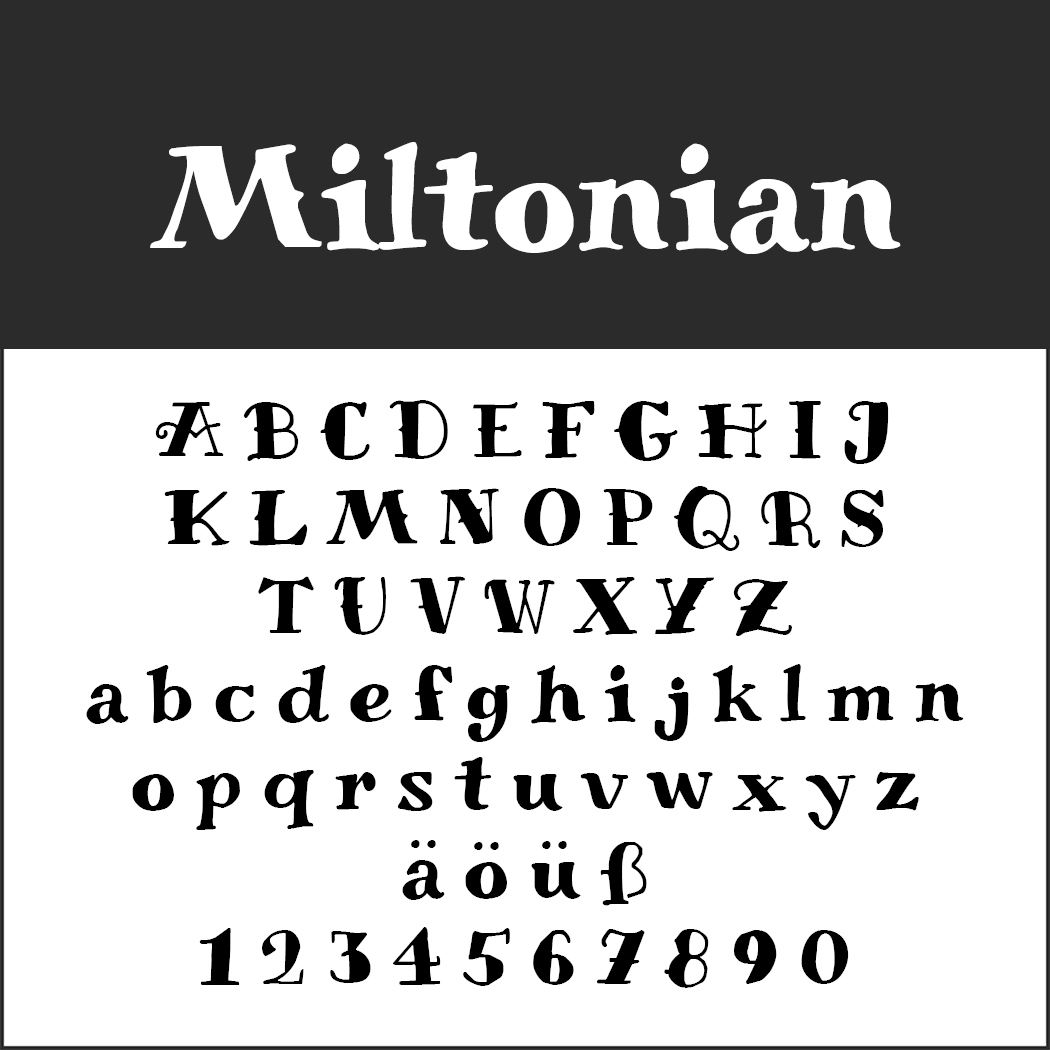
Haltung zeigen oder das eigene Lebensmotto nach außen tragen: Buchstaben werden heute nicht mehr nur gebraucht, um den Namen der Lieben auf dem Körper zu verewigen. Um so mehr Bedeutung gewinnen die Tattoo Schriftarten, mit denen die Textbotschaften auf die Haut kommen. Unter diesen gibt es zeitlose Klassiker und wechselnde Trends.
Vorwiegend plakativ in dicken Lettern präsentierten sich die Schriftzüge lange Zeit. Inzwischen sind auch filigrane Schriften durch feinere Nadeln möglich und vor allem bei Frauen sehr gefragt, die sie für ein diskretes Statement schätzen.
Klassiker bei Tattoos
Gothic– und Graffitischriftarten sowie gebrochene Schriften und Script-Fonts zählen zu den Klassikern im Tattoo-Bereich. Wir haben hier einige Beispiele zusammengestellt, die sich heute vielleicht nicht mehr so viele unter die Haut stechen lassen, aber sofort Assoziationen zu Tätowierungen wecken. Dieser Effekt kann in der Werbung genutzt werden, um auf bestimmte Angebote aufmerksam zu machen.
Tattoo SchriftartenTribal
Der Font ist dem Original VTC Tribal von WolfBainX nachempfunden.
Tattoo SchriftartenMiltonian
Die Schriftart in den zwei Schnitten Regular und Tattoo ist leicht verspielt und macht sich gut auf der Haut. Zudem ist kann sie für alles eingesetzt werden, das Tätowierungen imitieren soll.
Tattoo SchriftartenNew Rocker
Plakativ und laut trumpft dieser Font auf, der von Tattoos und Heavy Metal inspiriert ist.
Tattoo SchriftartenTeitheas
Die Vorlage für diesen Tattoo-Font wurde mit dem Stift von Hand geschrieben.
Rothenburg Deorative
Detailreich gestaltete Versalien sind bei Rothenburg Decorative der Hingucker.
Tattoo SchriftartenHeidorn Hill
Eine gebrochene Schrift, wie sie auch heute noch typisch für Tattoos sind.
Dustismo Roman
Hierbei handelt es sich nicht um einen expliziten Tattoo-Font, die Schrift eignet sich aber hervorragend dazu und überzeugt durch Understatement. Weitere Serifenschriften finden Sie unter Serifenschriften: Gratis-Fonts und Wissenswertes.
Tattoo Schriftarten – die neue Leichtigkeit
Geschwungene Schriften und Schreibschriften liegen zwar schon seit einiger Zeit im Trend, doch besonders grazile Fonts erfreuen sich erst in den letzten Jahren immer mehr an Beliebheit. Vier Beispiele haben wir für Sie hier bereitgestellt.
Tattoo SchriftartenFlaemische Kanzleischrift
Die elegante Kanzleischrift eignet sich sowohl für einzelne Wörter als auch ganze Sinnsprüche.
Tattoo SchriftartenAdine Kirnberg
Sehr beliebt bei Tattoo-Trägern: Adine Kirnberg ist schwungvoll und nostalgisch, kommt selbst bei kleinen Schriftgrößen groß raus.
Tattoo SchriftartenChopin Script
Etwas kräftiger als Adine Kirnberg aber auch von schöner Leichtigkeit präsentiert sich Chopin Script.
Scriptina
Elegante Unbekümmertheit springt uns hier ins Auge, die vor allem durch die ausladenden Ober- und Unterlängen erzeugt wird.